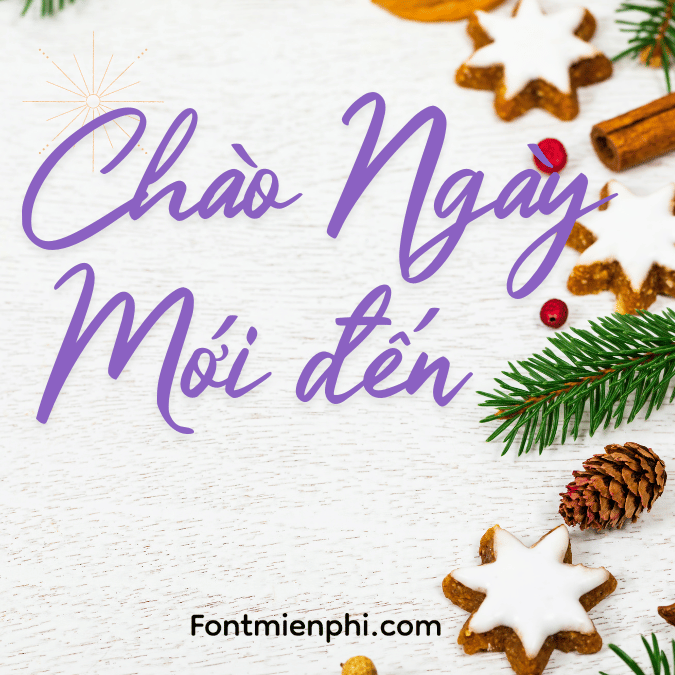
Việt hóa font 1FTV VIP Firegoods ,font Tết
Việt hóa font 1FTV VIP Firegoods
“Bùng cháy cùng từng con chữ”
ĐẶC ĐIỂM NỔI BẬT
• Phong cách Grunge mạnh mẽ: Nét chữ góc cạnh với hiệu ứng cháy xém tự nhiên
• Hiệu ứng lửa động: 3 phiên bản hiệu ứng (Lửa cháy – Tàn lửa – Khói đen) tích hợp sẵn
• Tối ưu cho Gaming & Esports: Hỗ trợ đầy đủ bộ dấu tiếng Việt + ký tự đặc biệt
ỨNG DỤNG ĐỈNH CAO
✓ Thiết kế logo đội tuyển Esports
✓ Poster phim hành động/kinh dị
✓ Banner quảng cáo sự kiện âm nhạc
✓ Bao bì sản phẩm năng lượng
BỘ VIP “INFERNO EDITION”
4 phiên bản độc quyền:
• Regular (nét chuẩn)
• Burn (hiệu ứng cháy 50%)
• Scorch (hiệu ứng cháy rụi)
• Neon (phát sáng trong bóng tối)
“Firegoods – Thổi bùng sức mạnh thiết kế của bạn!”
PHỐI MÀU CHUẨN PRO
• Màu chính: Đen #000000 + Cam lửa #FF4500
• Hiệu ứng: Outer glow màu plasma
• Kết hợp: Hình ảnh vết nứt dung nham